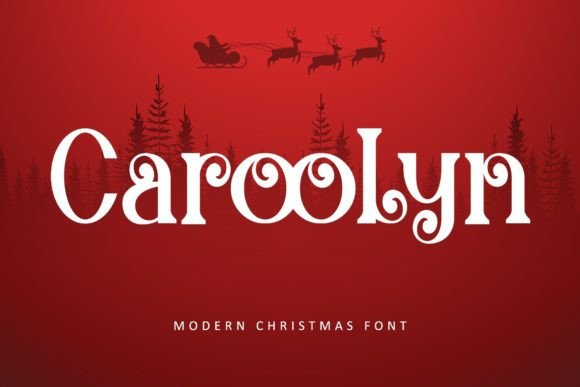
Carolyn - Fuente manuscrita para invitaciones y tarjetas de felicitación
Carolyn es una fuente manuscrita informal, diseñada con un estilo limpio, moderno y femenino. Su estilo fluido y manuscrito aporta a los diseños un toque lujoso, suave y personal, ideal para branding moderno, papelería de bodas, frases para redes sociales, tarjetas de felicitación o productos de marca femeninos. Como fuente manuscrita con encanto y elegancia, Carolyn aporta personalidad y calidez a proyectos digitales e impresos.
Esta fuente destaca por sus letras suaves y fluidas y su estética de firma, lo que la hace ideal para logotipos, empaques, invitaciones y cualquier diseño que busque un toque artesanal o elegante. Aporta una sensación orgánica y humana de la que carecen muchas fuentes decorativas o de exhibición.
- Estilo de escritura elegante: aporta un toque personal y artesanal a los diseños.
- Agrega calidez y personalidad en comparación con las fuentes genéricas: ideal para marcas artesanales y hechas a mano.
P: ¿ Caroolyn es adecuado para textos corporales o párrafos largos?
R: No realmente. Su estilo de escritura a mano funciona mejor en tamaños grandes, encabezados, títulos, logotipos o texto decorativo en lugar de bloques largos de texto. -